Internationale Finanzmedien und Blogger warteten gestern gespannt auf die Entscheidung des indischen Finanzministeriums, welche Form das neue Währungssymbol für die Rupie haben wird. Am Abend dann die Meldung, dass sich Finanzminister Pranab Mukherjee noch etwas Zeit erbete, um über die 5 nominierten Entwürfe zu entscheiden. Zudem habe Premierminister Manmohan Singh die Wahl des Symbols zur Chefsache gemacht.
Tage zuvor machten Designer im Land darauf aufmerksam, dass sie zwar nominiert seien, Ihr Entwurf aber nicht unter den veröffentlichten zu finden sei (ein Beispiel zeigt die Abbildung rechts). »Mein Entwurf ist nicht unter den fünf in den Medien verbreiteten Alternativen. Ich weiß nicht, was da los ist.« sagte die Architektin Nondita Correa-Mehrotra gegenüber dem Finanzblog Rediff.com. Nach Aussagen der Rediff-Redaktion sei ihr Entwurf einer der besten: elegant, sofort zu verstehen und sowohl im Druck als auch handschriftlich gut einzusetzen.
Im März 2009 berichtete ich hier im Fontblog über den Wettbewerb …. : Wie würdet Ihr ein Symbol für die Rupie gestalten? Die Rupie ist eine der wichtigsten Währungen der Welt und will sich mit einem exklusiven Schriftzeichen in die Riege von Dollar, Pfund und Euro einreihen. Es solle leicht zu schreiben sein sowie den Geist und die Kultur Indiens widerspiegeln.
[Update] Erik Spiekermann hat mir gerade diese Skizze mit folgenden Worten gemailt: »Habe gerade meine alte skizze zum Rupee gefunden. Das hatte ich mal am telefon geschmiert, während mich ein journalist vom BBC dazu interviewte. Es könnte eigentlich ganz schnell gehen, wenn es keine auftraggeber gäbe … ;)«.
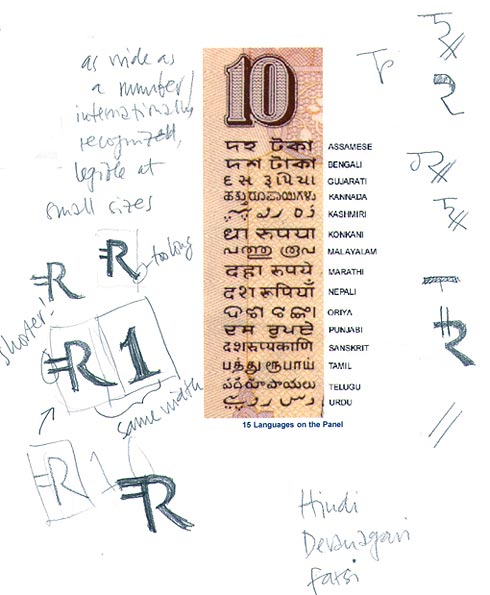
Es scheint, als ob weiterhin die graphische Schnittmenge aus lateinischen R und dem Ra (nicht Ru) aus Devanagari (र) und Gujarati (ર ) mit zwei Querstrichen beliebt ist, denn die Kandidaten 2, 4 und 5 – wenn es denn die echten Finalisten sind – bilden alle dieses Prinzip auf leicht unterschiedliche Weise ab. Ein westlicher Fontdesigner würde U+20A8 (₨) dann wohl mit einem R ohne Stamm und (unten rechts) mit Querstrich(en) generieren, damit es zu den arabischen Ziffern und lateinischen Buchstaben passt.
Dass ein bis in den letzten Winkel vorgegebenes Symbol sich nicht durchsetzt, weil es nur alleinstehend funktioniert, haben wir mit dem Eurozeichen (U+20AC, €) hinlänglich erlebt, sodass ich hoffe, dass die Inder daraus gelernt haben.
Der obige Vorschlag von Frau Correa-Mehrotra wirkt auf mich weder indisch noch europäisch, sondern eher nach Katakana. Das „Parken verboten“ (1) wird es wohl kaum werden.
Nur zur Hintergrundinfo: es gibt vier weitere Rupee-Zeichen, die schon in Unicode codiert sind: